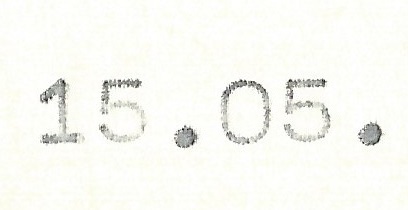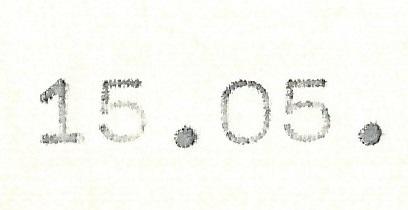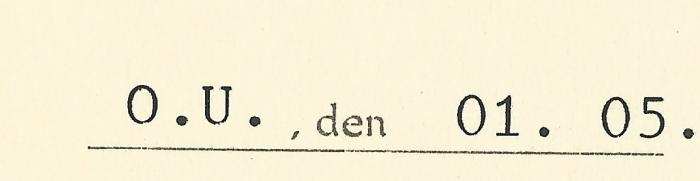
Was welcher Zeit könnte diese Schrift stammen?
Was welche Zeit könnte diese Schrift stammen? Kann man sogar das Land bestimmen?
PS: Braubt ihr noch weitere Scanns?
Meinst du die Schreibmaschinenschrift oder den Vordruck?
Das ist eine "Pica".
Beispiel:
Kann aber auch ne Prestige Elite sein:
Ist ja praktisch die gleiche Schrift, nur eben andere Größe: 12pt = Elite, 10pt = Pica. Diese Schriften wurden eigentlich von allen Schreibmaschinen-Herstellern angeboten.
Der saubere, gleichmäßige Anschlag lässt auf eine elektrische Schreibmaschine schließen, die sauberen Glyphenkanten machen ein Carbon-Farbband (also eines auf Filienband statt den älteren Gewebebändern) sehr wahrscheinlich.
Der Name und der sonstige Text lassen auf eine zumindest deutschsprachige Quelle schließen, sodass Schreibmaschinen der Marken Adler, Olympia, Olivetti oder auch IBM in Frage kommen, etwa im Zeitraum zwischen mitte der 1960er bis etwa mitte der 1980er Jahre. Genaueres würdde nur ein direkter Typenvergleich des Schriftbildes der betreffenden Maschinen  ergeben. Sachverständige dieser Zeit besaßen oft ausführliche Schriftmustersammlungen diverser Schreibmaschinen-Modelle, anhand sderrer man die verwendete Mschine leicht identifizieren konnte.
Kann man eigentlich eine Schreibmaschine von heute damit ausschließen?
Wenn die Frage ist, ob auszuschließen sei, dass das Dokument gestern erstellt worden wäre, dann ist die Antwort nein. Schreibmaschinen sind ziemlich robuste Apparate ;)
Kann aber auch ne Prestige Elite sein …
Ist ja praktisch die gleiche Schrift, nur eben andere Größe: 12pt = Elite, 10pt = Pica. Diese Schriften wurden eigentlich von allen Schreibmaschinen-Herstellern angeboten.
Nö, die beiden unterscheiden sich (f, i, die Serifen …).
Erst mit den elektronischen Schreibmaschinen wurden drei standardisierte Größen eingeführt: 10, 12 und 15 Zeichen pro Zoll (CPI). Manche Hersteller von Schreibmaschinen lieferten auch mechanische Schreibmaschinen mit anderen Größen aus. Die häufigste Standardgröße war jedoch 10 CPI in der Schriftart Pica. Es gab aber auch Maschinen mit 12 CPI, hierfür wurde meist die Schriftart Elite verwendet. Obwohl die Schriftart Pica sich sicherlich auch verkleinert mit 12 CPI verwenden lassen würde, bezeichnet man mit Pica und Elite auch die Schriftdichte, unabhängig von der verwendeten Schriftart. Die Schriftart Prestige Elite hat also 12 CPI und Prestige Pica hat 10 CPI, obwohl die Schriftart Prestige der Schriftart Pica nicht sehr ähnelt. Schriftarten in 15 CPI werden auch als Micron bezeichnet.
Ursprünglich waren das also die reinen Bezeichnungen für Schriftarten, später hat sich die abgeleitete gleichlautende Größenangabe eingebürgert
Kann man eigentlich eine Schreibmaschine von heute damit ausschließen?
Es gibt sicher auch heute noch Schreibmaschinen mit der Pica als Schriftart.
Kann man eigentlich eine Schreibmaschine von heute damit ausschließen?
Wenn das jedoch bedeutet: Eine heute hergestellte Schreibmaschine, dann ebenso nein, denn die Verkaufszahlen an Schreibmaschinen sind seit der Abhör-Berichte über NSA und Co wieder deutlich gestiegen. In vielen Firmen werden dinge, die Geheim bleiben sollen wieder mehr auf Schreibmschinen geschrieben, und die noch existierenden Schreibmaschinen Hersteller haben wieder lukrative Verkaufszahlen.
Und damit gibt es dann durchaus auch wieder neue Maschinen mit Pica als Schriftart.
Wenn die Frage ist, ob auszuschließen sei, dass das Dokument gestern erstellt worden wäre, dann ist die Antwort nein. Schreibmaschinen sind ziemlich robuste Apparate ;)
der Zonk wartet eben überall. :hammer:
Gruß Schlutup
Hätte da noch ein weiteres Dokument von dem Herren :)
Zeitraum?
Hätte nicht gedacht, das man es doch einigermaßen eingrenzen kann. TOP!
Ich hab natürlich ein paar Info zu den Dokumenten, wollte es aber erst am Schluss damit raus kommen.
Damit alle Wege offen sind und nicht gleich alles in eine Richtung geht. Ich hoffe ihr seit mir nicht Böse.
DANKE
So, jetzt ist da so eine Semi-Sans, die ich jetzt nicht finden konnte. Zumindest bin ich mir recht sicher, das hier keine IBM-Kugelkopf mit einem original Kugelkopf dran beteiligt war, denn hier geht die mittlere Zacke des W nicht bis zur Versalhöhe.
Auf der Seite von Ransmayer-Rodrian, die auch heute noch Schreibmaschinenschriften produzieren, lassen sich alte Kataloge herunterladen.
Leider zeigen die Schriftproben nicht das komplette Alphabet. Die mittlere Zacke des W geht aber bei einigen Serifenlosen bis zur Versalhöhe.
Im Katalog von 1932 gefällt mir die „Moderne Blockschrift“ Ra 280 auf Seite 18a sehr. Gibt es eine vergleichbare digital?
Wow! :biglove: Das ist ja mal ne prima Quelle für einen Bereich der „Spezial-Schriftgießereien“ die aus den üblichen für Satzlettern herausfallen, obzwar auch diese Schreibmschinenschriften angeboten haben.
So weit ich weiß, gibt es relativ wenige Digitalisierungen nach Originalunterlagen der Typenhersteller.
könnten die beiden Schriften auch in der DDR entstanden sein?
DDR-Schreibmaschinen wurden auch mit geändertem Gehäuse unter dem Namen Sigma in der BRD verkauft oder waren Lizenzprodukte von Olivetti. Daher lässt sich das wahrscheinlich nicht klar festlegen.